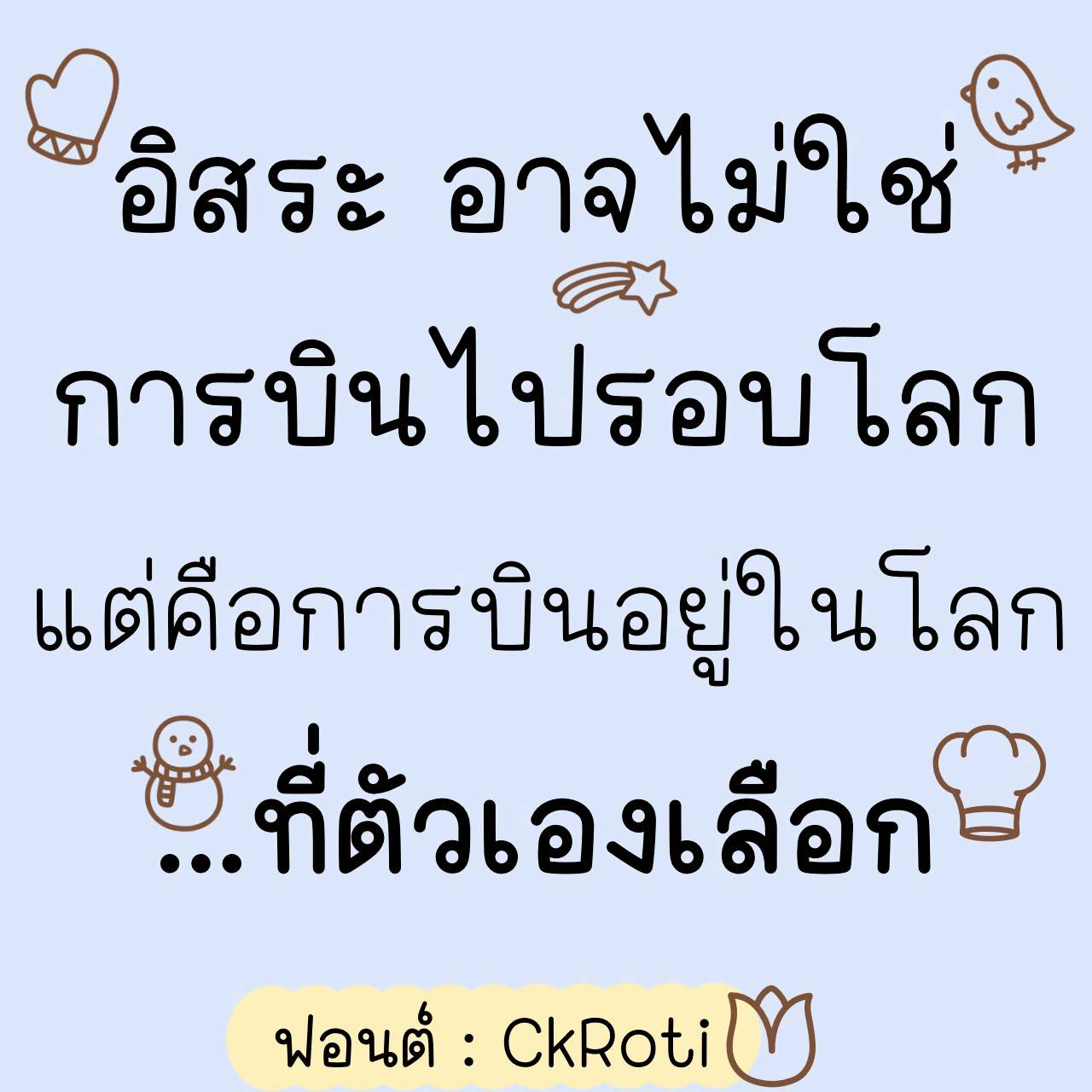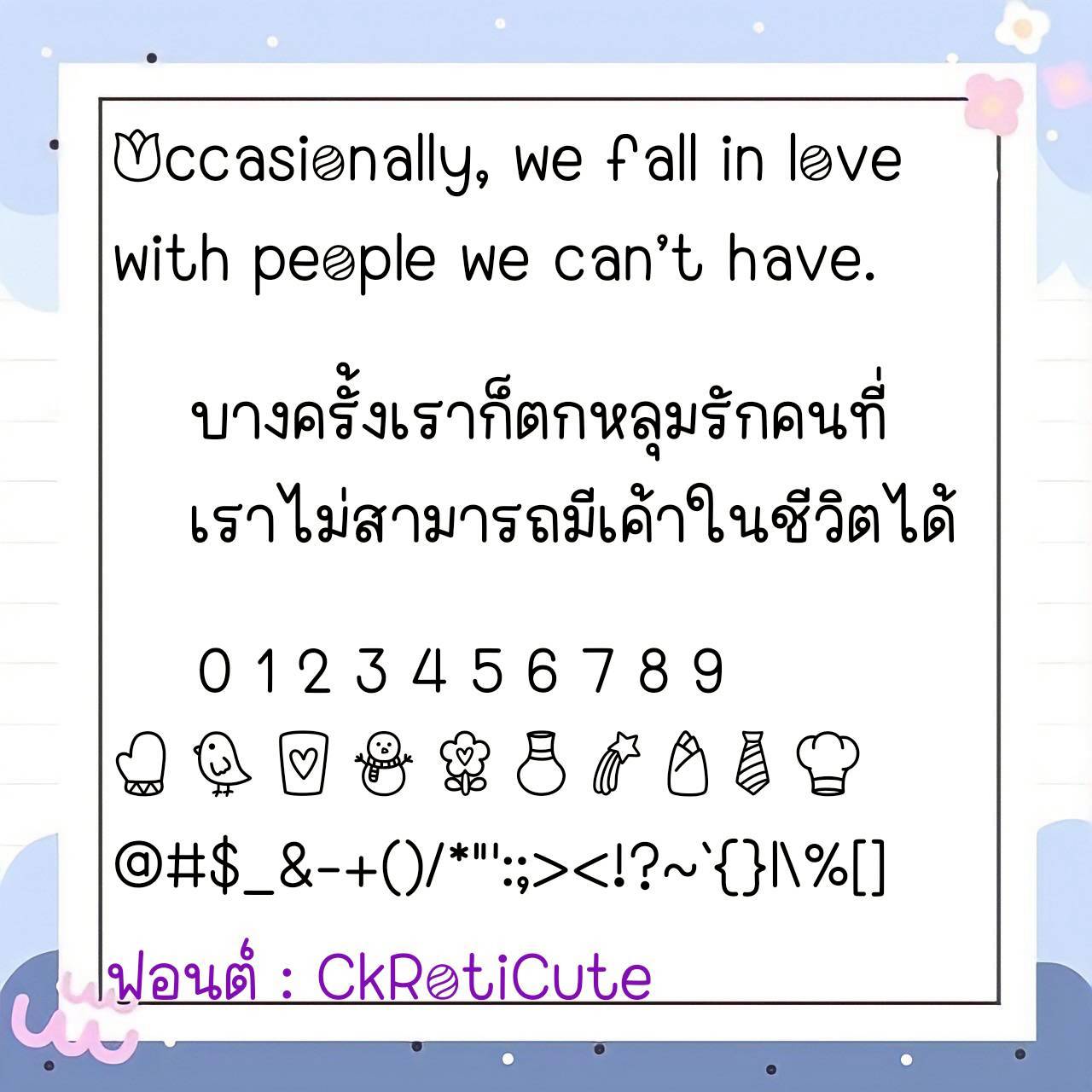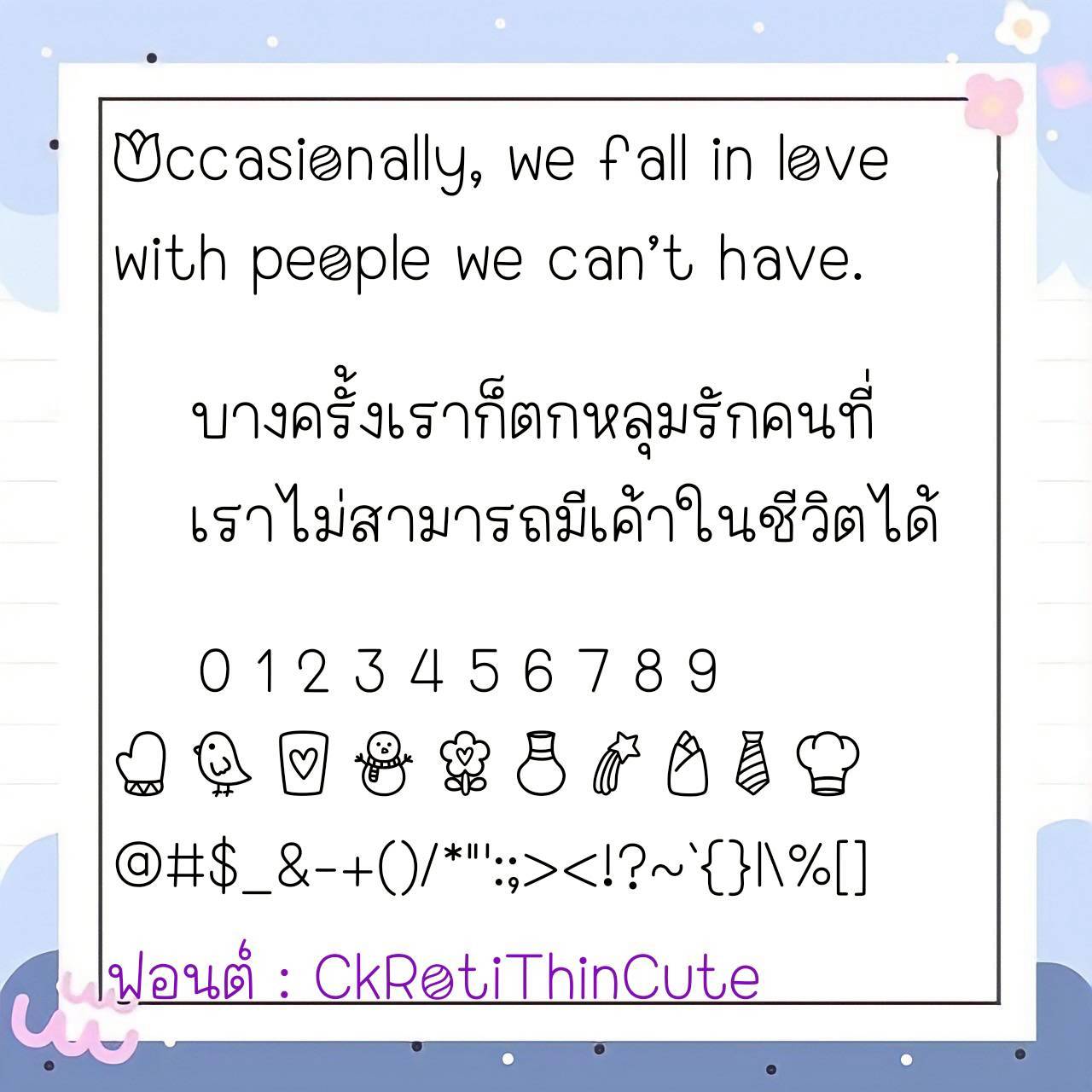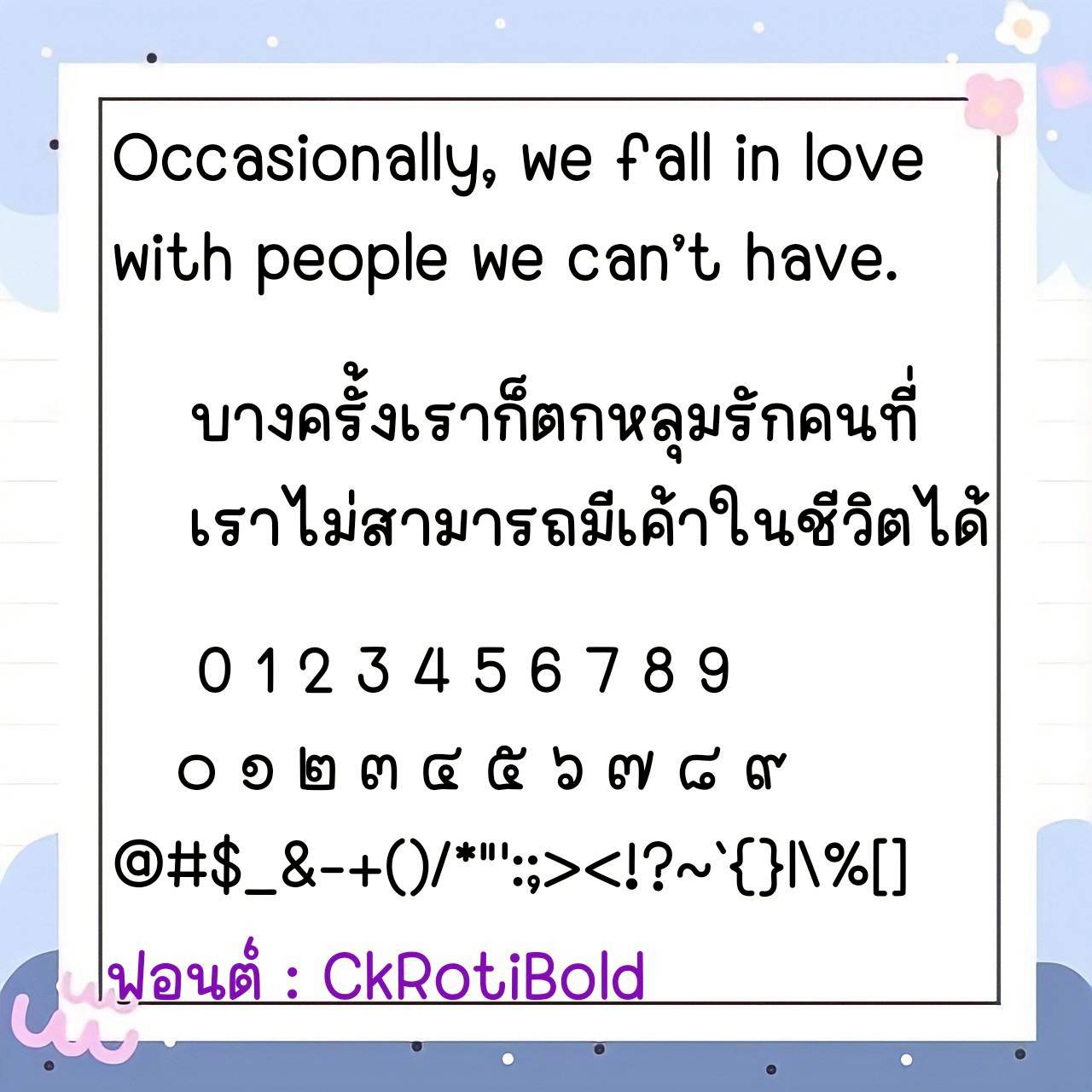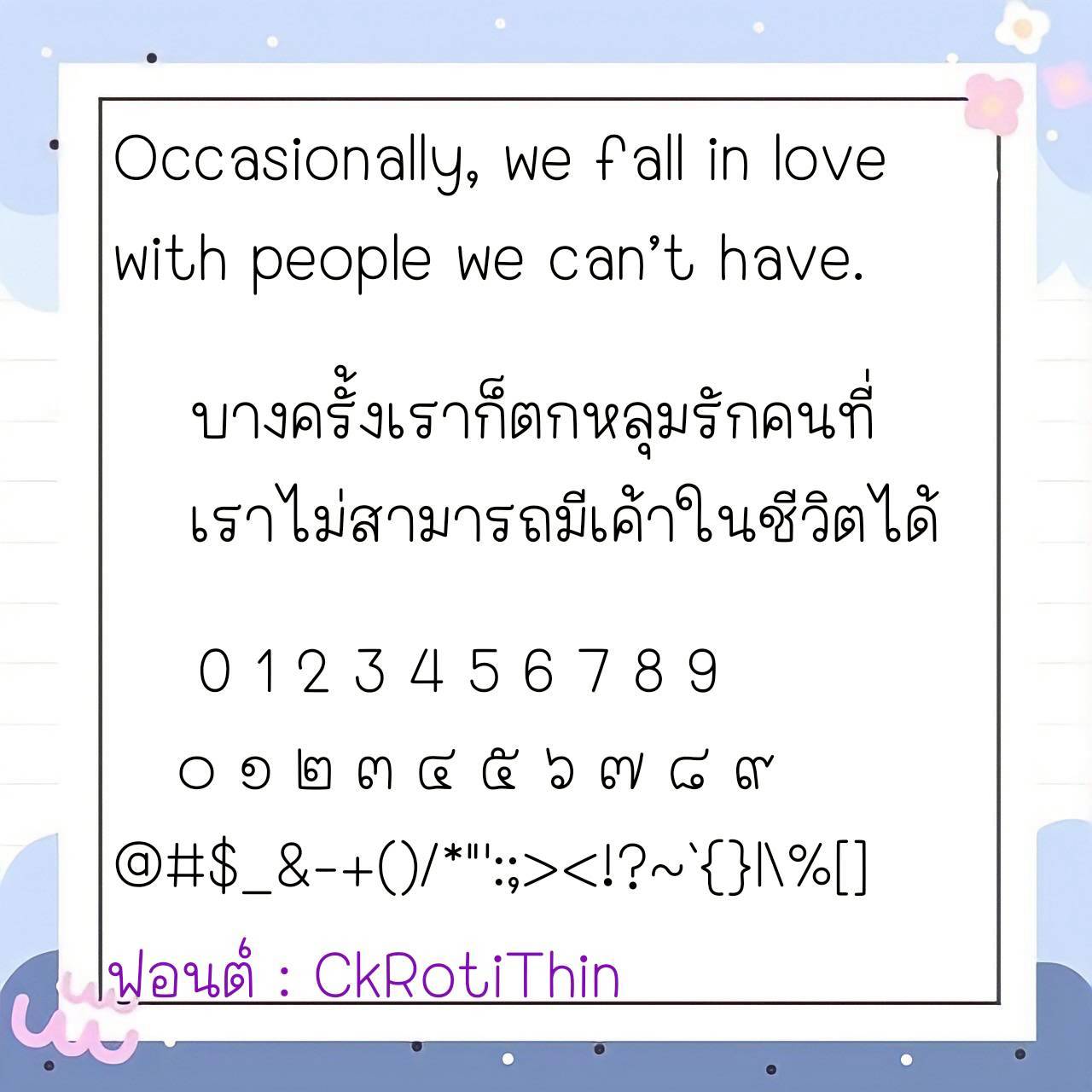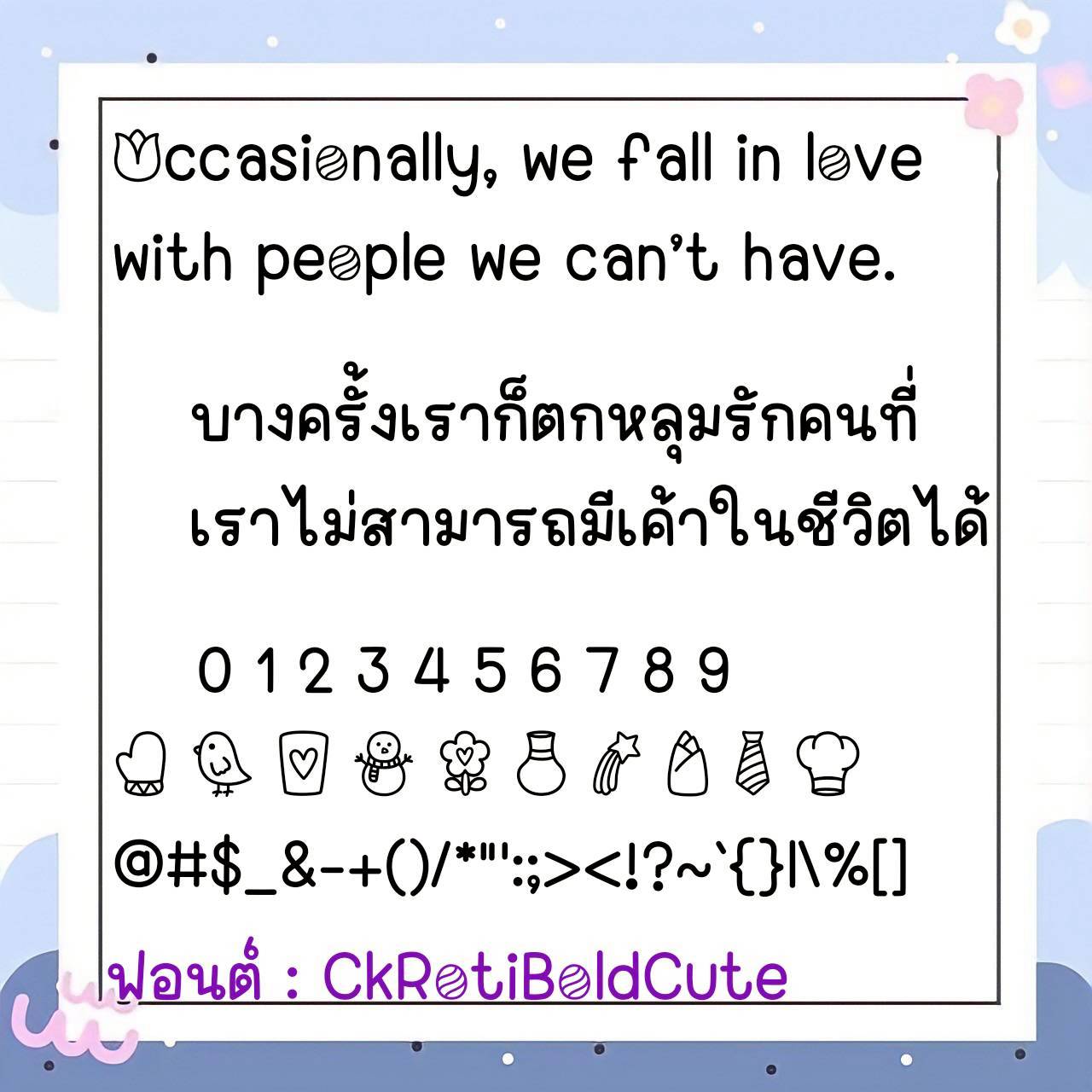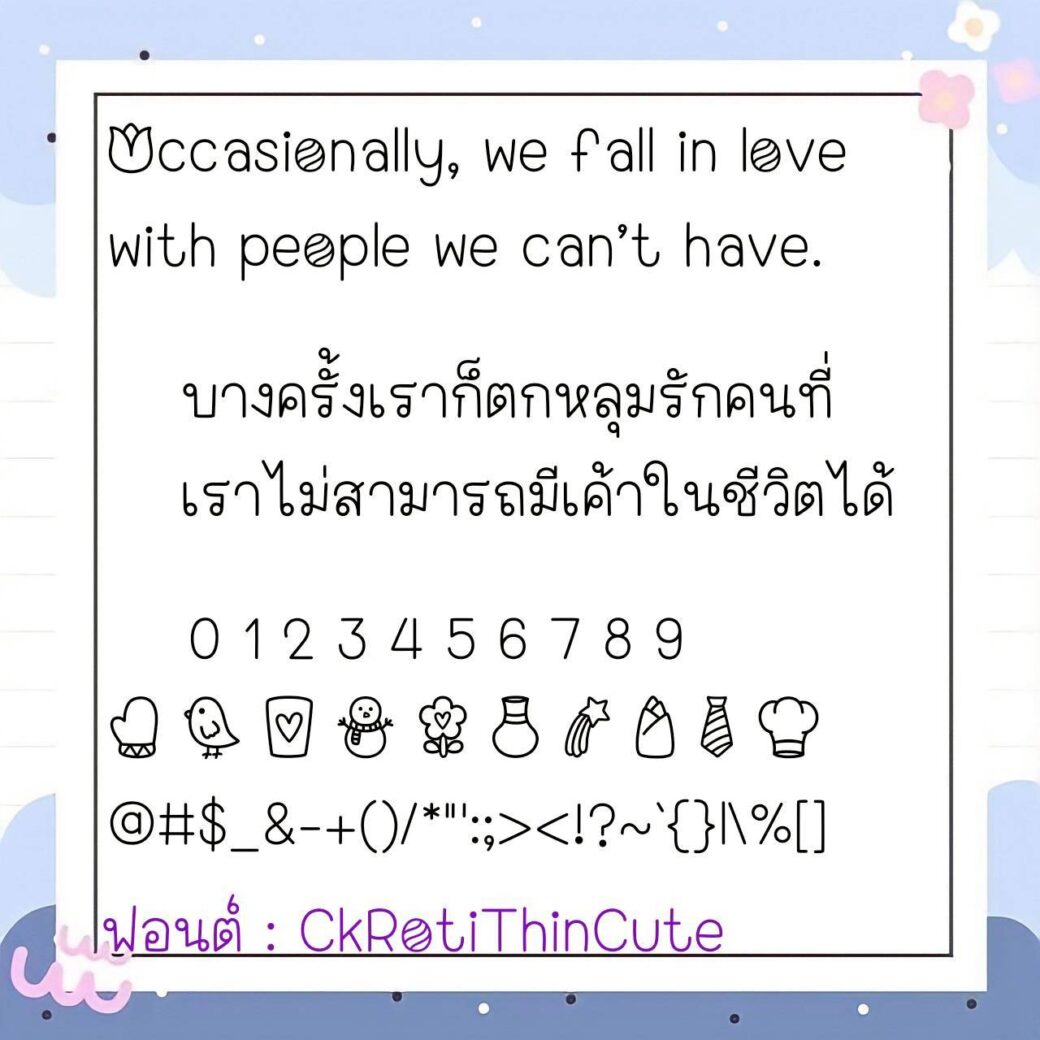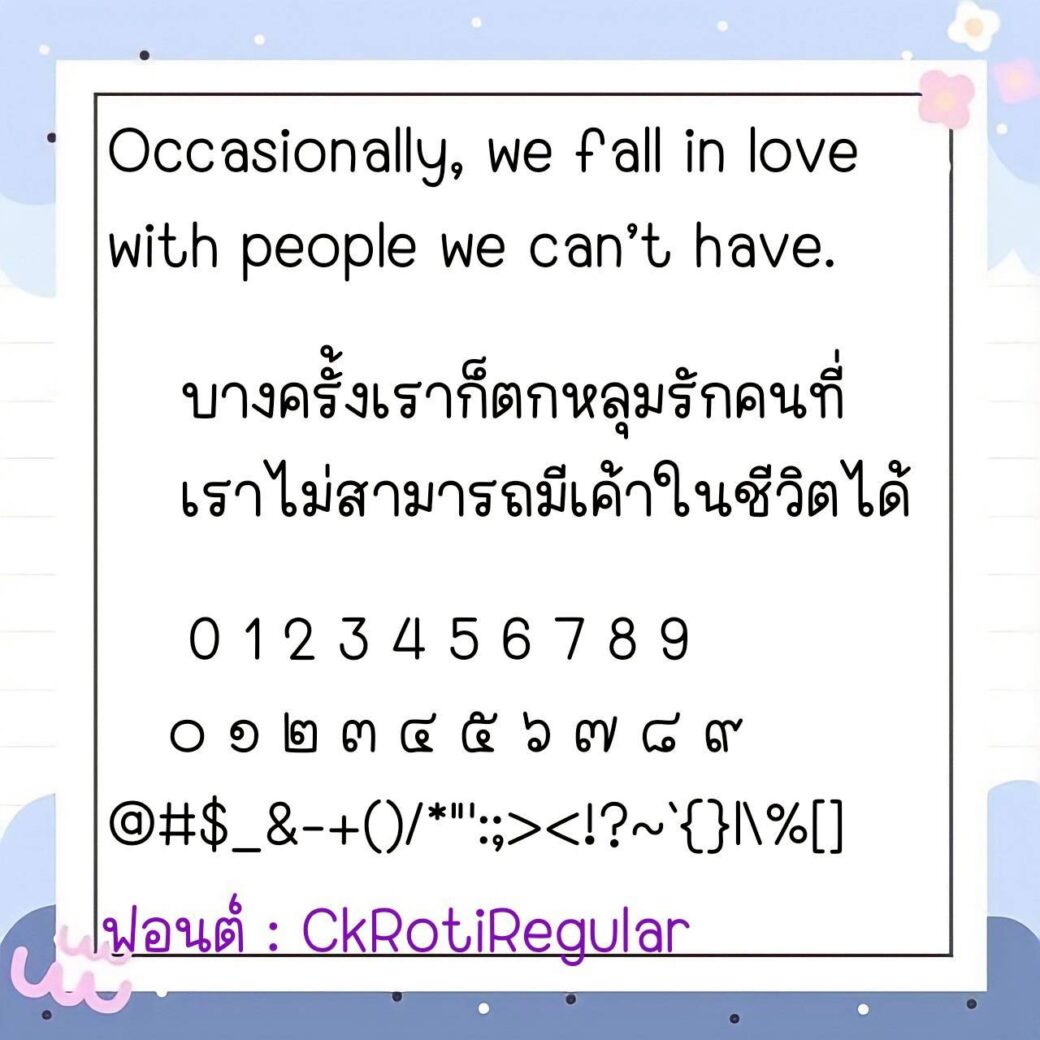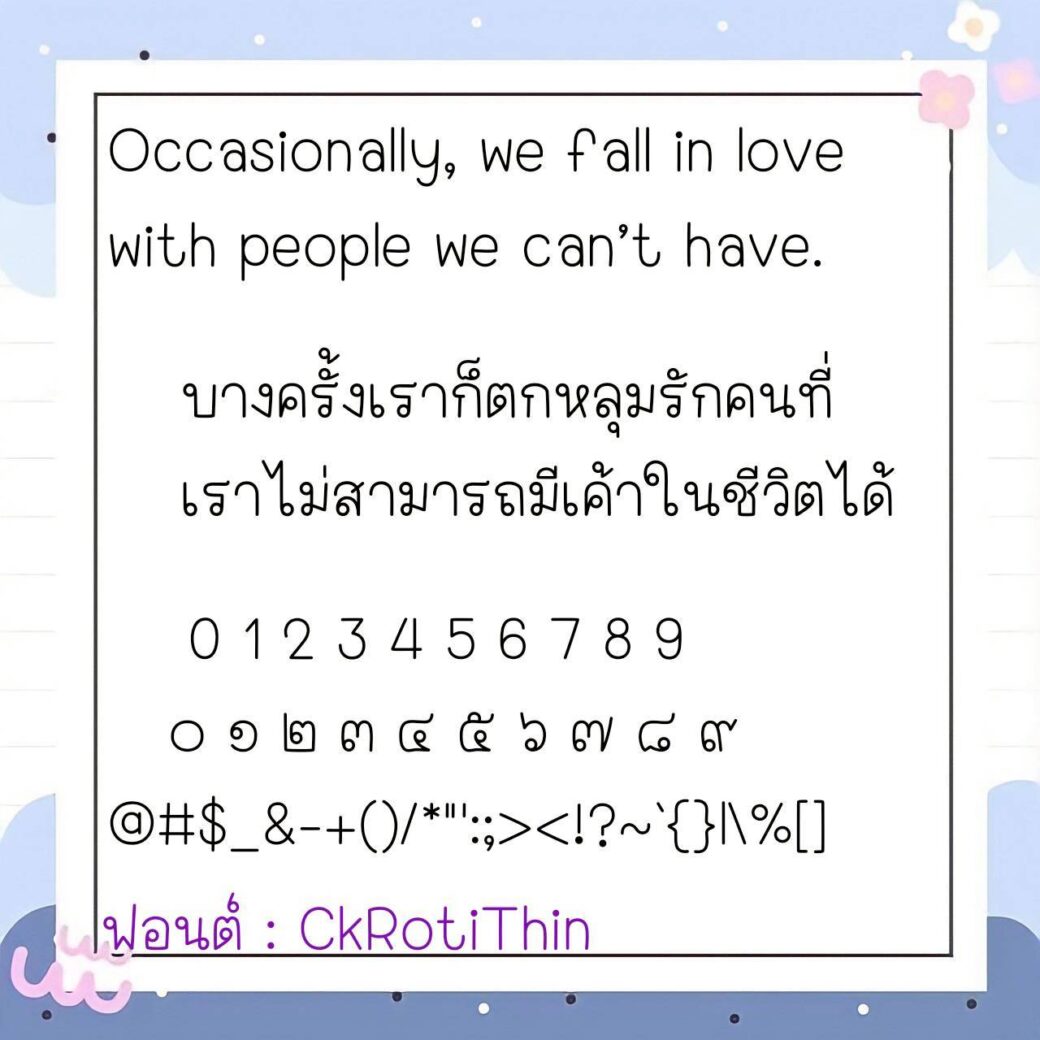
Font CkRoti
ชื่อสินค้า : Font CkRoti 💙
🔸 ฟอนต์ลายมือตัวอ้วนใหญ่ มีความน่ารักกึ่งวัยรุ่น เน้นอ่านง่ายสบายตาเช่นเดิม และยังมีไฟล์อิโมจิน่ารักๆ ที่ใช้แทนเลขไทยให้ด้วยค่ะ 🥰💙
🔹 This handwritten font is chubby and has a cute, youthful vibe, focusing on easy readability and a comfortable viewing experience. It also includes cute emoji files that can be used to replace Thai numerals. 🥰💙